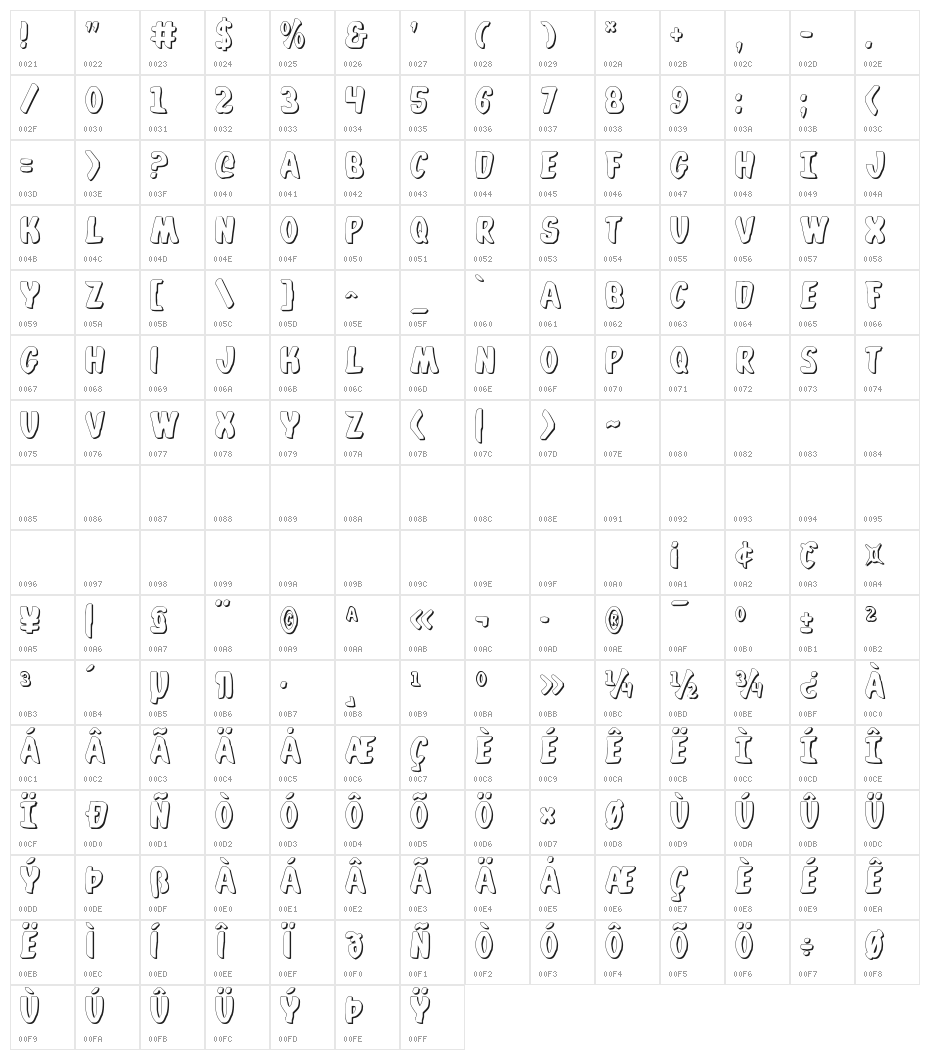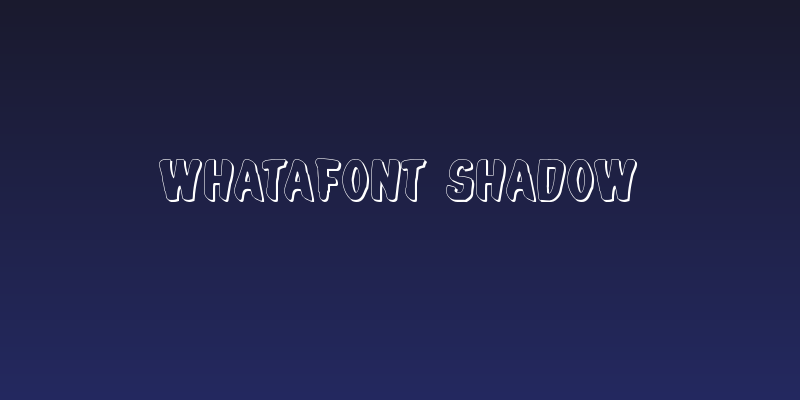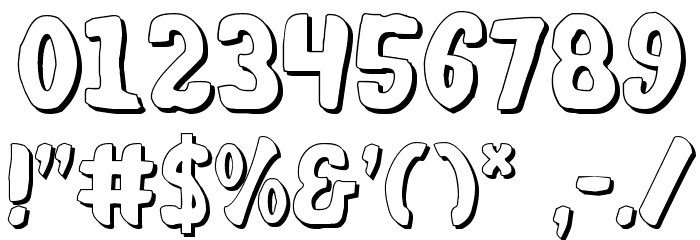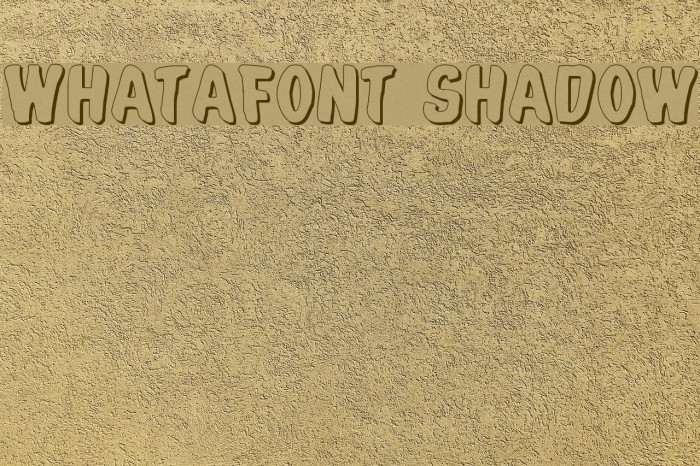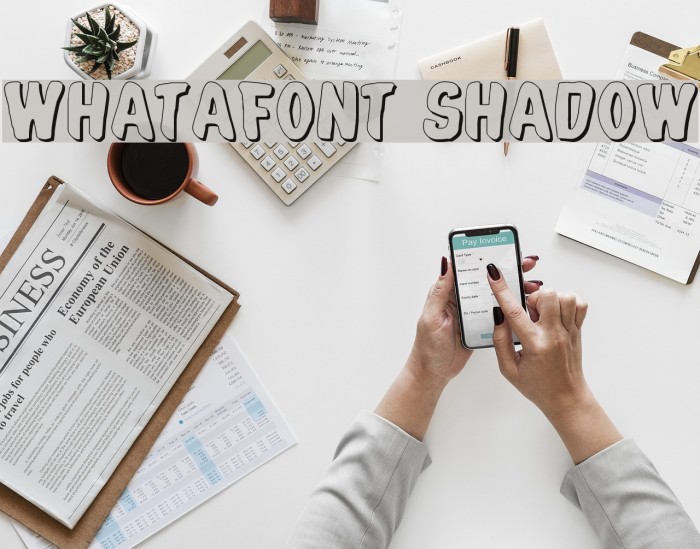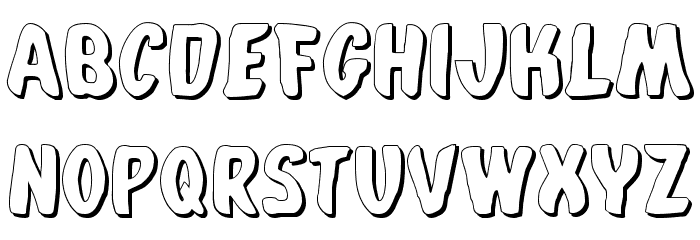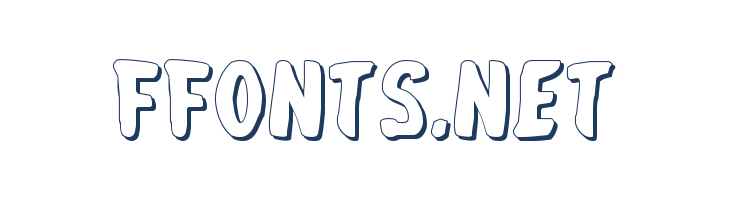
Whatafont Shadow Font
| Estilo general | Playful, Cartoonish |
| Proyectos propuestos | Ideal for children's books, comic strips, playful branding, and eye-catching posters. |